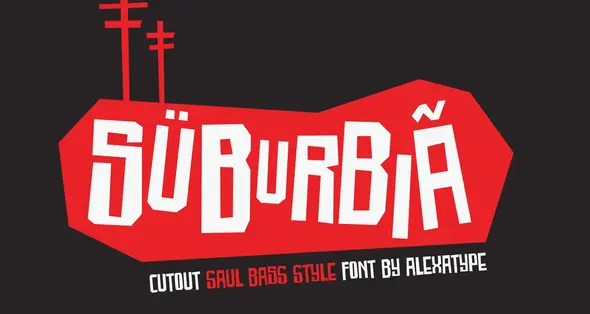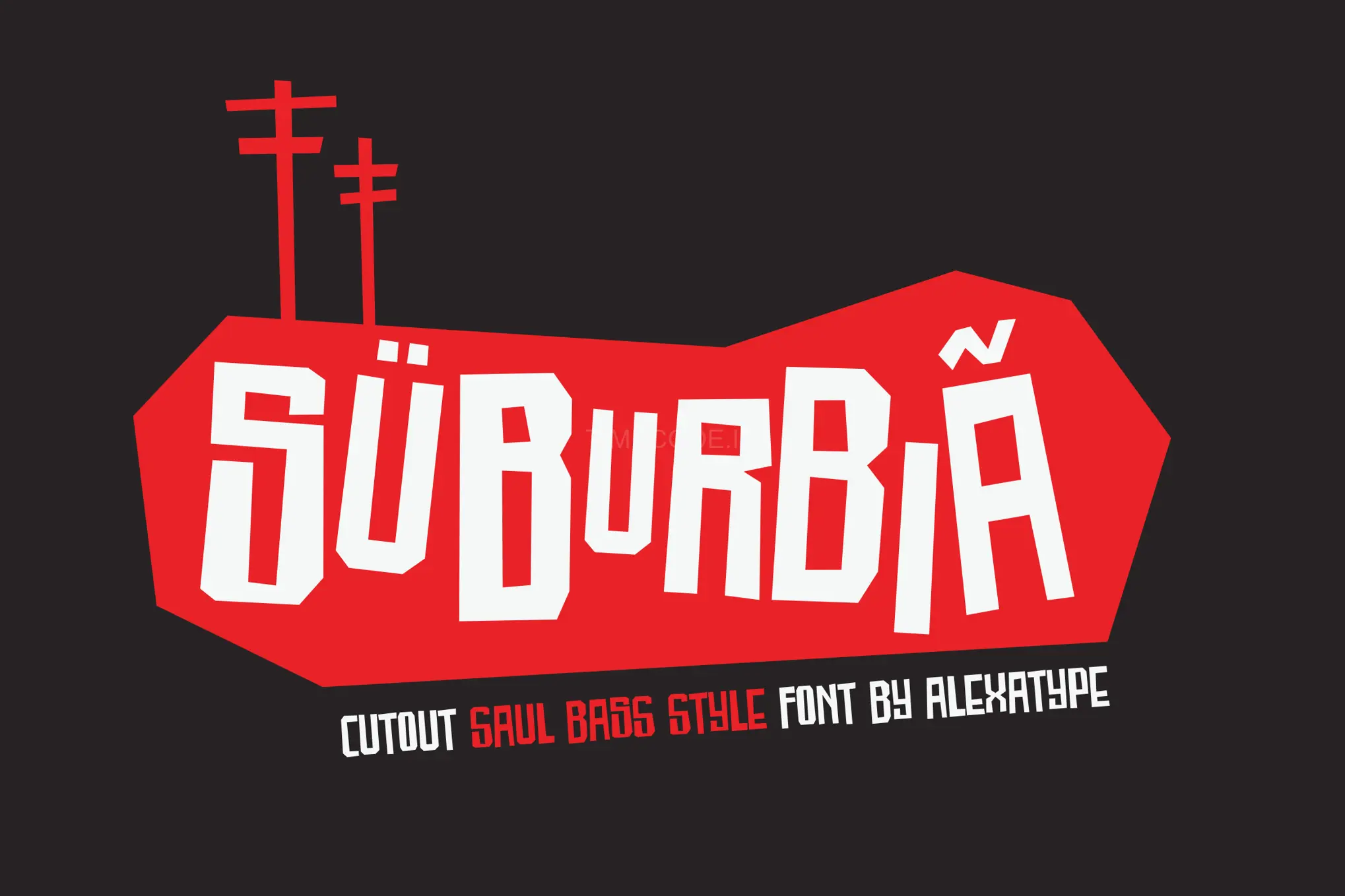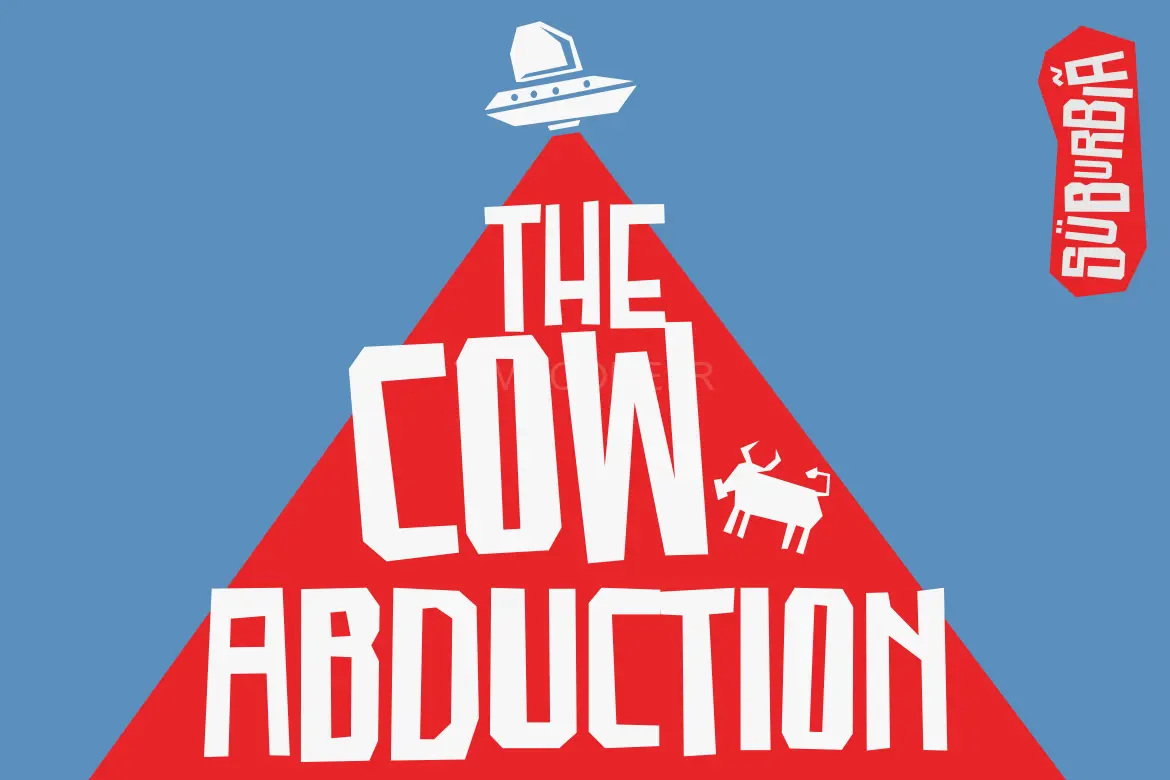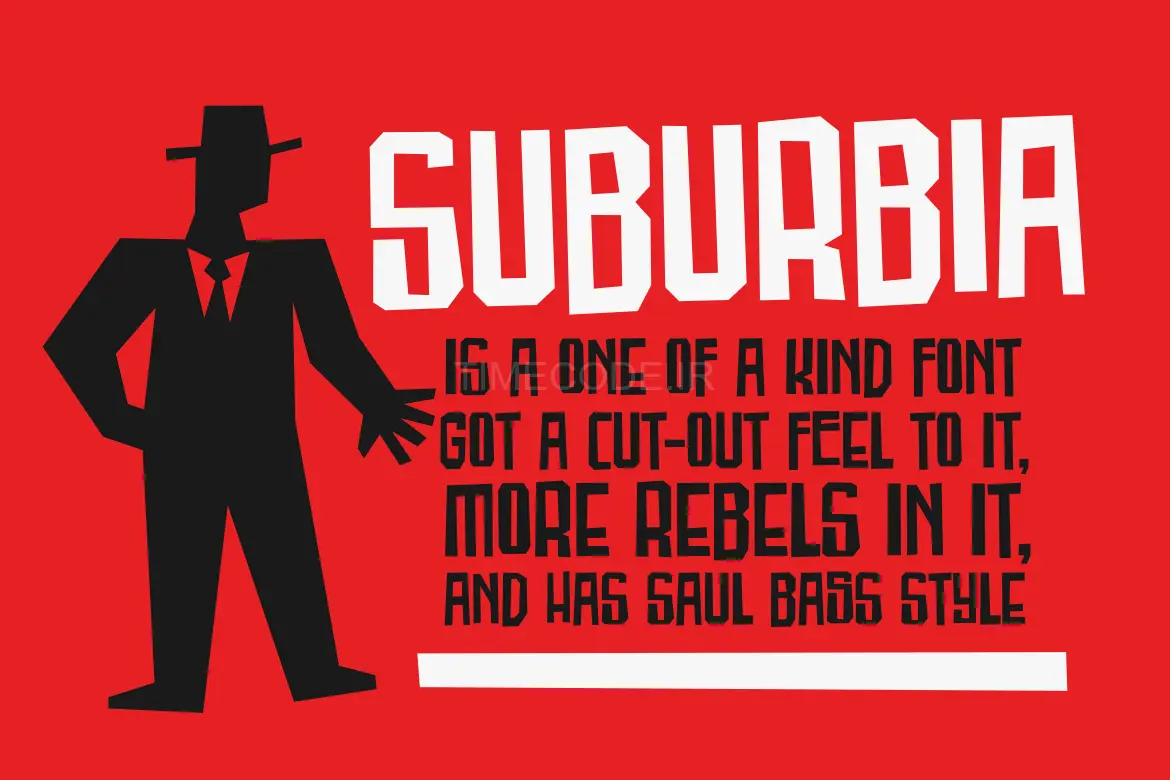
• SUBURBIA - Cutout Saul Bass Style Font
مورد استفاده پیشنهادی: سایز های بزرگ مانند پوستر و بیلبورد (Display / Poster)
سابربیا، با ظاهری ساده و غیررسمی، اشکال هندسی و حس برش‌خورده.
مناسب برای انتقال پیامی قدرتمند در پروژه شما.
introducting SUBURBIA
SUBURBIA, using simple, casual appearance, geometric shapes and cut-out feel.
Perfect to deliver a powerful message on your project.